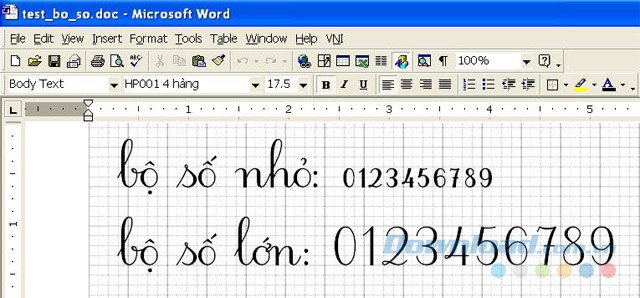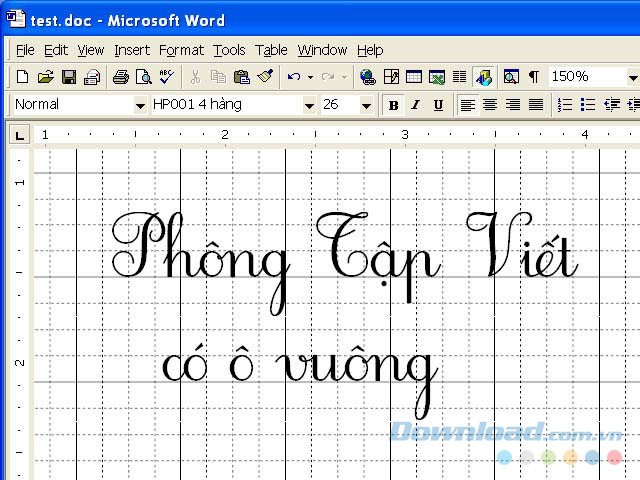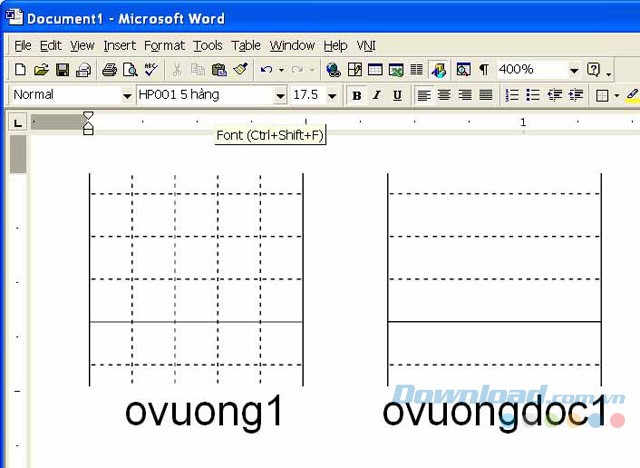
Font Chữ Tập Viết Tiểu Học: Hỗ Trợ Luyện Chữ Cho Trẻ
chính là bộ font tiếng Việt được thiết kế đặc biệt để hỗ trợ trẻ em luyện viết. Đây là công cụ hữu ích cho học sinh lớp 1 và các em học sinh tiểu học trong quá trình rèn luyện kỹ năng viết chữ.
Mặc dù hiện nay có rất nhiều tài liệu tập viết khác nhau, bạn hoàn toàn có thể tự tạo ra các trang chữ viết mẫu cho con em mình bằng cách sử dụng bộ font này. Font chữ tập viết Tiểu học tuân thủ nghiêm ngặt các quy định về chữ viết do Bộ Giáo dục và Đào tạo ban hành.
Font chữ tập viết Tiểu học
Lợi Ích Khi Sử Dụng Font Chữ
Bộ font này giúp học sinh hình thành thói quen viết chữ đúng ngay từ những nét cơ bản. Các chữ cái được thiết kế với tỉ lệ chuẩn, đảm bảo độ cao, độ rộng và khoảng cách giữa các chữ cái hợp lý.
Cùng với đó, bộ font còn cung cấp hướng dẫn về nét chữ một cách rõ ràng. Nhờ vậy, học sinh có thể luyện tập từng nét chữ một cách chính xác, cải thiện kỹ năng nối nét và uốn lượn, đồng thời viết đúng theo mẫu chữ chuẩn của giáo trình tiểu học.
Việc luyện tập với font chữ này không chỉ giúp cải thiện chữ viết mà còn phát triển sự tỉ mỉ, kiên nhẫn và khả năng quan sát chi tiết ở trẻ. Đây là nền tảng vững chắc cho việc học tập và rèn luyện chữ viết đẹp trong tương lai.
Phân Loại Font Chữ Theo Khối Lớp
Bộ font chữ Tiểu học hỗ trợ cả giáo viên và học sinh trong việc lựa chọn font chữ phù hợp với từng độ tuổi và trình độ học tập.
Font chữ được phân loại theo từng khối lớp, từ lớp 1 đến lớp 5, với các nét chữ và kích thước khác nhau, phù hợp với từng giai đoạn phát triển kỹ năng viết. Học sinh mới bắt đầu sẽ được sử dụng font chữ lớn, rõ nét, trong khi học sinh các lớp cao hơn sẽ luyện tập với font chữ chuẩn và tinh gọn hơn.
Tính năng này đảm bảo quá trình luyện viết diễn ra hiệu quả, giúp từng học sinh tiến bộ theo khả năng riêng, đồng thời hỗ trợ giáo viên soạn bài tập và giáo án một cách chính xác.
Các đặc điểm nổi bật của bộ font chữ luyện viết Tiểu học
Chữ viết chuẩn mực: Đây là yếu tố then chốt. Bộ font này cung cấp các mẫu chữ viết tay và chữ in tuân thủ nghiêm ngặt các quy định về kích thước, độ nghiêng và khoảng cách, hỗ trợ học sinh hình thành kỹ năng viết chữ đẹp và chính xác ngay từ đầu.
Sự đa dạng về kiểu chữ: Các font luyện viết thường bao gồm nhiều phiên bản khác nhau như chữ in thường, chữ in hoa, chữ viết thường và chữ số, tạo điều kiện cho học sinh được học tập và thực hành một cách toàn diện.
Chức năng nét đứt: Nhiều bộ font được trang bị phiên bản nét đứt, giúp giáo viên và phụ huynh dễ dàng tạo ra các bài tập tô chữ. Điều này hỗ trợ học sinh làm quen với hình dáng của từng chữ cái, từ đó xây dựng thói quen viết đúng nét và đúng thứ tự.
Tích hợp kẻ ô ly: Một số font chữ đặc biệt còn được tích hợp sẵn kẻ ô ly, mô phỏng chính xác vở tập viết của học sinh. Tính năng này rất hữu ích trong việc tạo tài liệu luyện tập và đảm bảo các chữ được viết đúng vị trí, đúng tỷ lệ trên dòng kẻ.
Bộ font chữ tập viết hiện có hai loại chính: 4 hàng và 5 hàng:
Loại 4 hàng tương ứng với tập học sinh 4 ô ly, tuy nhiên, có thể không hiển thị được đầy đủ các ký tự đặc biệt như Ô, Ắ... Bộ font này bao gồm 4 file:
Font chữ tập viết Tiểu học
Bộ nét chữ này sở hữu vẻ đẹp tinh tế và đạt chuẩn mực cao, do đó, phụ huynh có thể hoàn toàn tin tưởng khi tải về để giúp con em mình rèn luyện kỹ năng viết chữ đẹp.